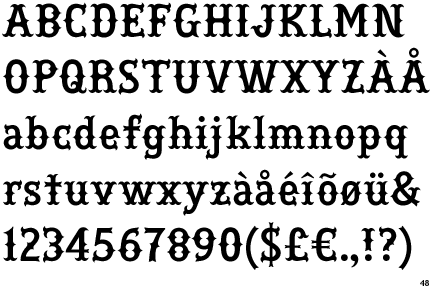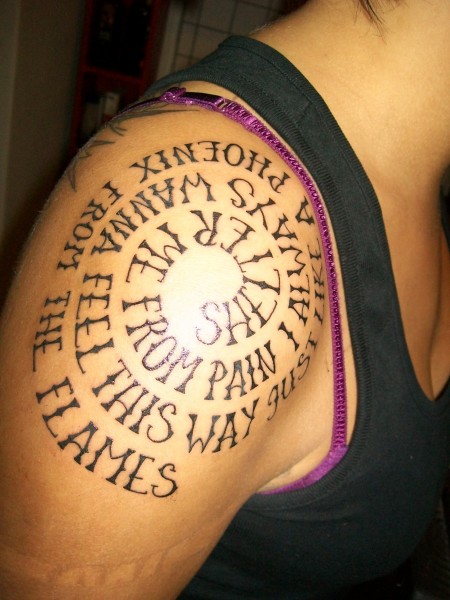
Suche diese Schrift einer Tätowierung
ich bin verzweifelt auf der Suche nach der Schrift dieses Tattoos. Mehr als das Bild selbst habe ich leider nicht.
Habe schon jede Menge Datenbanken durchsucht, zwar ähnliche aber nicht ganz diese gefunden.
Wäre super wenn jemand näheres wüsste.
Und als entfernte Inspiration könnte so etwas wie die Hessian gedient habenHessian.gif
Ist übrigens die Hauschrift einer etwas rustikakeren Bruderschaft :-)
Die Originalhausschrift ist aber etwas älter als die Hessian von Madtype. Die Hessian kam erst viel später nach. Toskanische Egyptienne, Tuscan ... sind angemessene Suchworte.
Das ist ja fast dieselbe Schrift nur etwas breiter, mit der Vorlage und dem Hinweis die Buchstaben noch etwas schlanker zu machen sollte der Tattoomann das hinbekommen.
Ich weiß auch nicht, warum man mit der Hessian die Schrift besser nachempfinden können sollte als mit dem Foto. Das muss eh handgezeichnet werden und entweder kann er das oder nicht  :-?
Na ja, wenn der Tattooman sich eine Transferfolie von der am Rechner gesetzten Schrift zieht und das Bild dann auf die Haut klebt, dann muss er einfach nur noch nachzeichnen. Freihand ist da schon ein anderer Schnack  – außer für so einen versierten Schriftenmaler wie Dich natürlich.  :-D
... von der am Rechner gesetzten Schrift ...
Aber das kann er ja mit der genannten anscheinend auch nicht ...
Problem ist dass ich ja einen völlig anderen Text möchte, daher wäre es schon nicht schlecht für eine grobe Vorlage wenigstens mal den Text in der richtigen Schrift zu habe. ;)
Wieviel Text ist denn das, vielleicht kann ich dir ja helfen?
Ganz konkret wäre das:
Jedem Anfang wohnt ein Zauber inne
der uns beschützt und der uns hilft zu leben.